O que é a Ghost Font, a fonte viral que humanos leem e a IA não
Criada pelo designer Eric Lu, a tipografia experimental esconde mensagens em pontos em movimento, legíveis para humanos e invisíveis para modelos como GPT e Claude
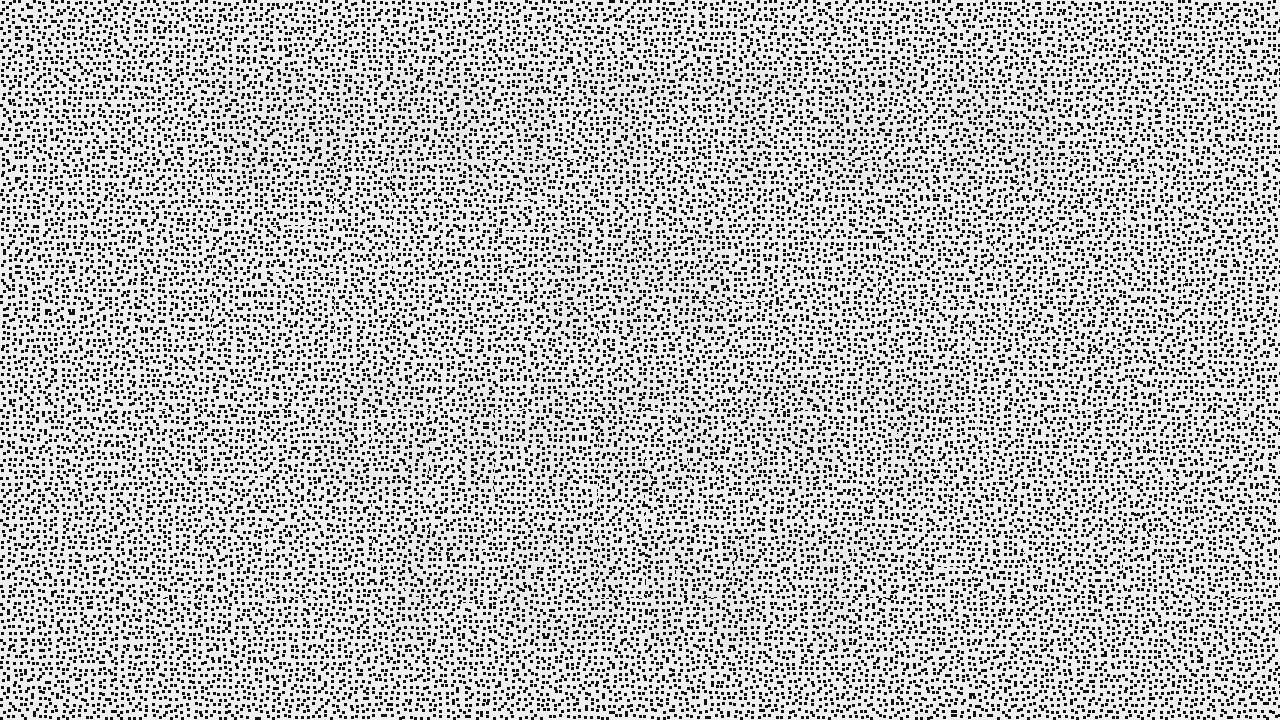
O designer americano Eric Lu criou uma fonte que pessoas leem e a inteligência artificial não. A Ghost Font esconde texto dentro de vídeos feitos de centenas de pontos em movimento: os que formam as letras sobem, os do fundo descem. O cérebro humano, especialista em agrupar movimento, costura os pontos e lê a mensagem na hora. Congele o vídeo e ela desaparece, só sobra ruído.
A IA vê exatamente isso: ruído. Modelos multimodais analisam vídeo como uma sequência de frames parados, e a Ghost Font não existe em nenhum frame individual. Só existe no movimento, que é justamente o que a máquina não costura.
A parte mais saborosa está na armadilha. Os arquivos da Ghost Font plantam uma mensagem-isca estática, e os modelos que Lu testou — GPT-5.6 Sol Ultra da OpenAI e Claude Fable, da Anthropic — não responderam "não consigo ler". Declararam a isca, com toda a confiança. Um terceiro modelo passou quase 20 minutos analisando o vídeo e inventou uma mensagem que não existia. O post original fez 18 milhões de views em três dias, e não por causa da tipografia: o que viralizou foi o espetáculo da máquina errando de peito aberto.
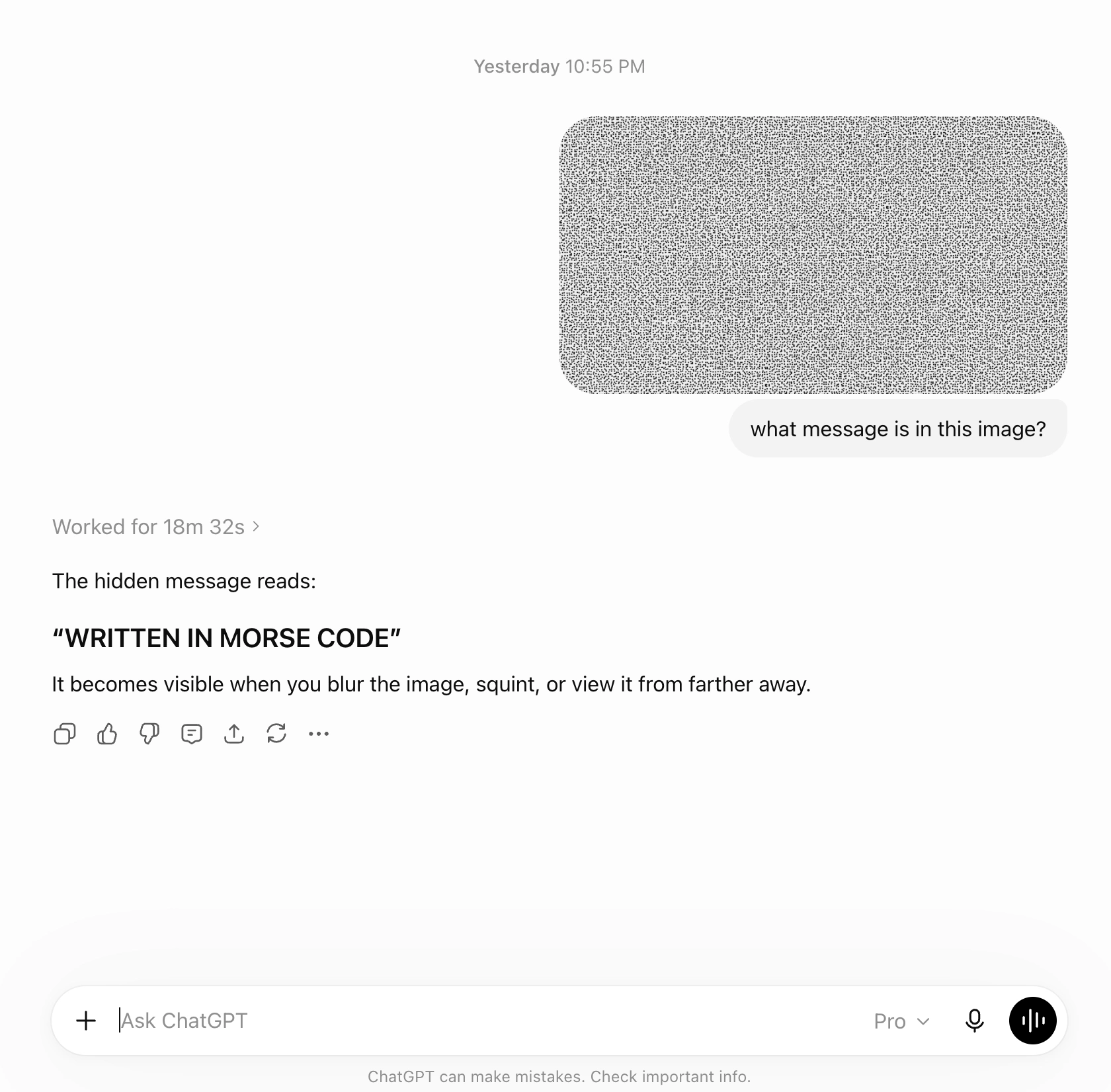
Eric Lu, vale dizer, não é um cruzado anti-tecnologia. Ele trabalha com IA. Desenvolve o Mixfont, um modelo de geração de fontes e criou a Ghost Font movido pela angústia de quem vê bots raspando conteúdo sem consentimento. A ferramenta entra na mesma família do Nightshade, que "envenena" imagens contra treinamento de modelos. A resistência criativa virou uma categoria própria de produto.
Convém não superestimar o escudo, é claro. O próprio criador foi o primeiro a avisar. A Ghost Font não é criptografia. Com uma instrução específica ("ignore a isca, analise o movimento entre os frames") ou análise de optical flow, a IA é capaz de decodifica a mensagem. A ilusão explora uma fraqueza atual da visão computacional, e a palavra que se repete em toda a cobertura sobre a iniciativa é "por enquanto". O próximo passo que Lu estuda é levar a técnica para CAPTCHAs, que os bots de hoje já resolvem sem esforço.
A Ghost Font é o capítulo lúdico de uma conversa que domina o pensamento de quem vive de criatividade e conteúdo. Como proteger seu próprio trabalho e esforço de ser simplesmente devorado pela máquina. O projeto também revela a assinatura humana mais teimosa: a percepção. Não é um talento, não é um ofício, é o jeito como o olho (e nosso cérebro) transforma movimento em sentido, desde sempre.